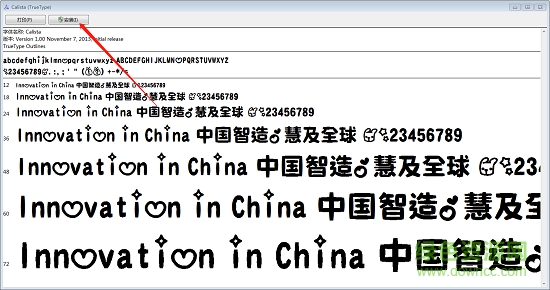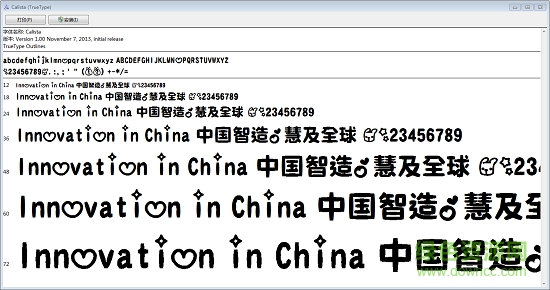
萌萌兔小貝字體是一款以可愛為主的中文字體,簡單的筆鋒能夠帶給用戶清新的字體,字體內(nèi)融入了眾多不同的特色標(biāo)簽,讓用戶在使用時能夠感受到更多不同的特色,需要的用戶快來綠色資源網(wǎng)下載吧!
萌萌兔小貝字體是一款非??蓯鄣闹形暮嗴w字體,你可以在比克爾下載這款萌萌兔小貝字體并安裝到電腦中,擁有非??蓯鄣淖煮w外觀,將字體中加入了星星、心形、兔子、巧克力等各種形狀,將漢字與圖畫融為一體,非常適合女生或少兒用戶使用。